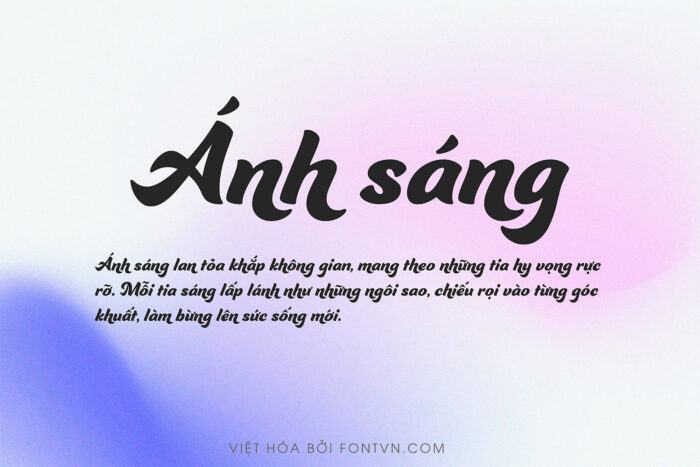
DVN Ganache Việt hóa – Font chữ Script vui tươi và năng động
DVN Ganache Việt hóa - Font chữ Script vui tươi và năng động
Font chữ Ganache là một kiểu chữ mang phong cách ngọt ngào và nổi bật, được thiết kế với các đường nét uốn lượn mềm mại. Nét chữ dày và tròn trịa, tạo cảm giác mượt mà và thân thiện. Font này sử dụng hiệu ứng gradient tinh tế, tạo ra sự chuyển đổi màu sắc mượt mà từ xanh dương sang tím hồng, mang lại một cảm giác hiện đại và tươi mới. Với thiết kế cách điệu và phần bóng đổ nổi bật, Ganache mang lại sự nổi bật cho tiêu đề hoặc các đoạn văn bản ngắn, lý tưởng cho các dự án thiết kế như poster, banner, tiêu đề video, hoặc logo.
Sự uyển chuyển trong từng nét chữ giúp Ganache phù hợp với các thương hiệu hoặc sản phẩm hướng đến giới trẻ hoặc các lĩnh vực sáng tạo. Các nét chữ mềm mại nhưng mạnh mẽ của font cũng làm tăng tính dễ đọc, phù hợp cho cả in ấn và thiết kế số.